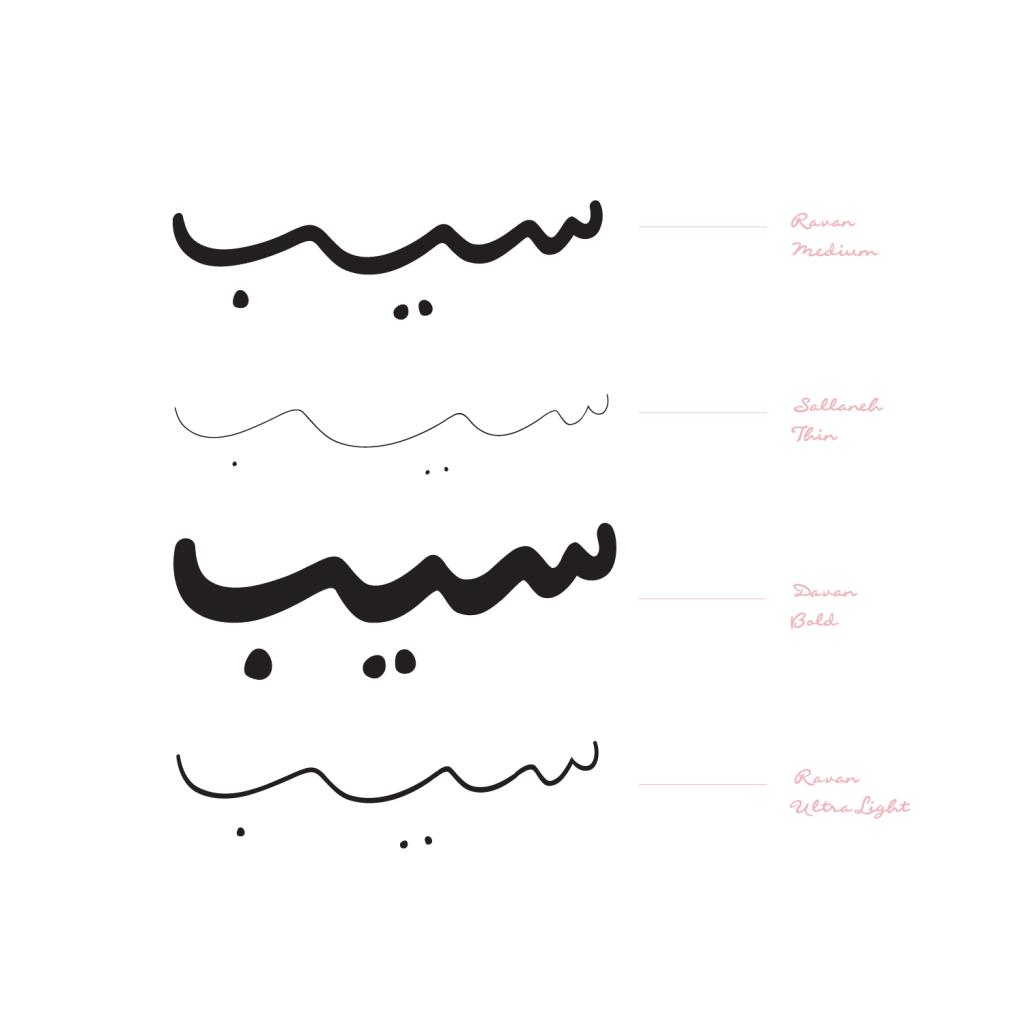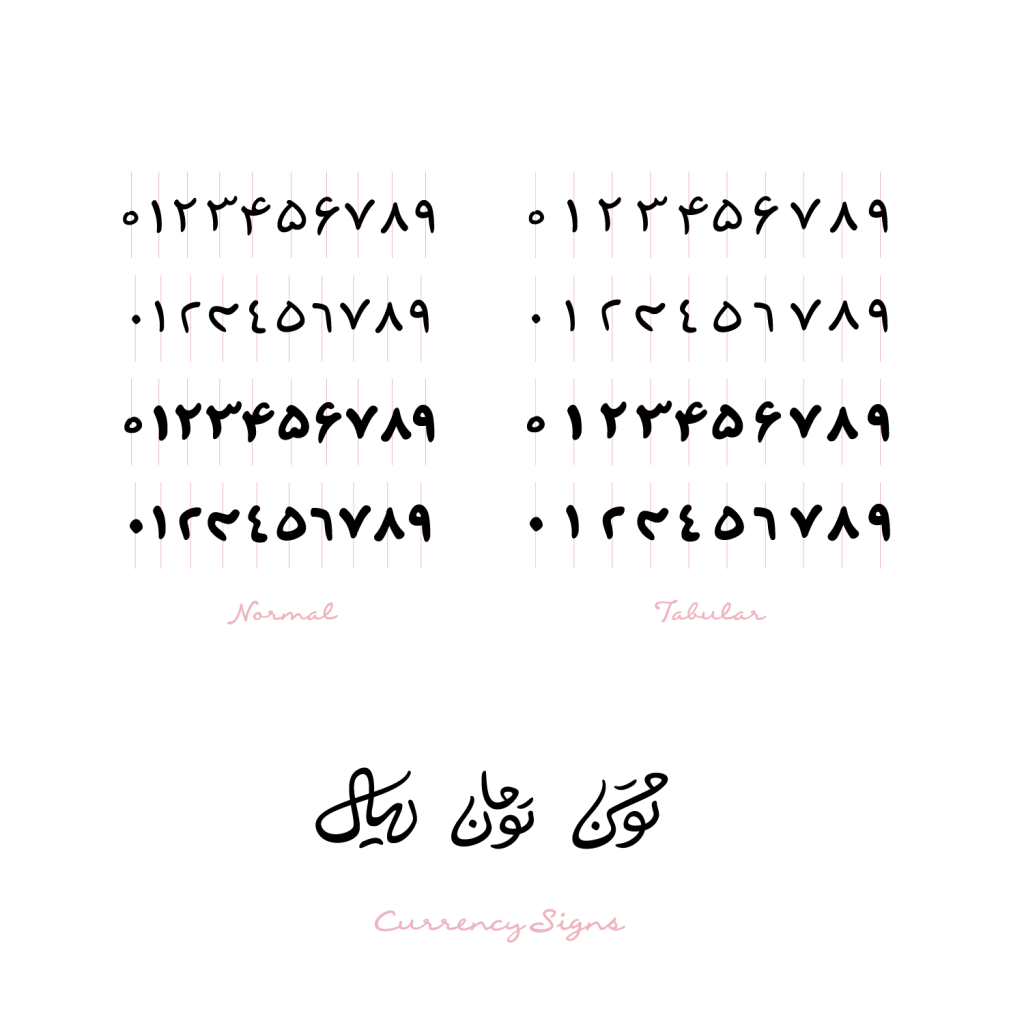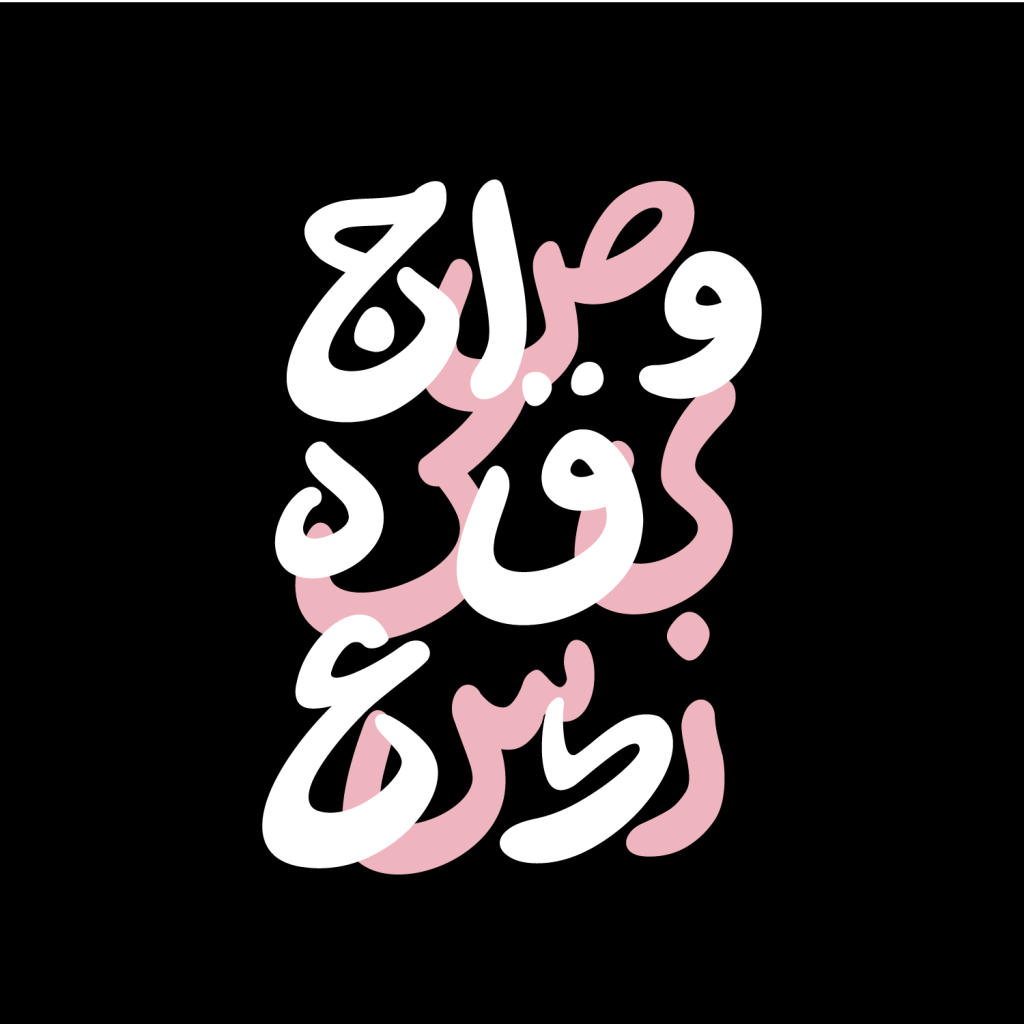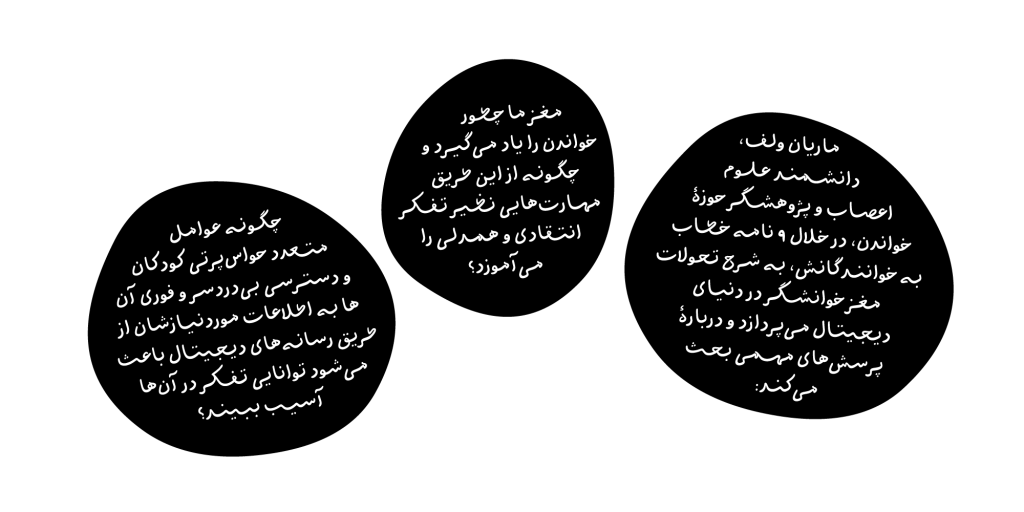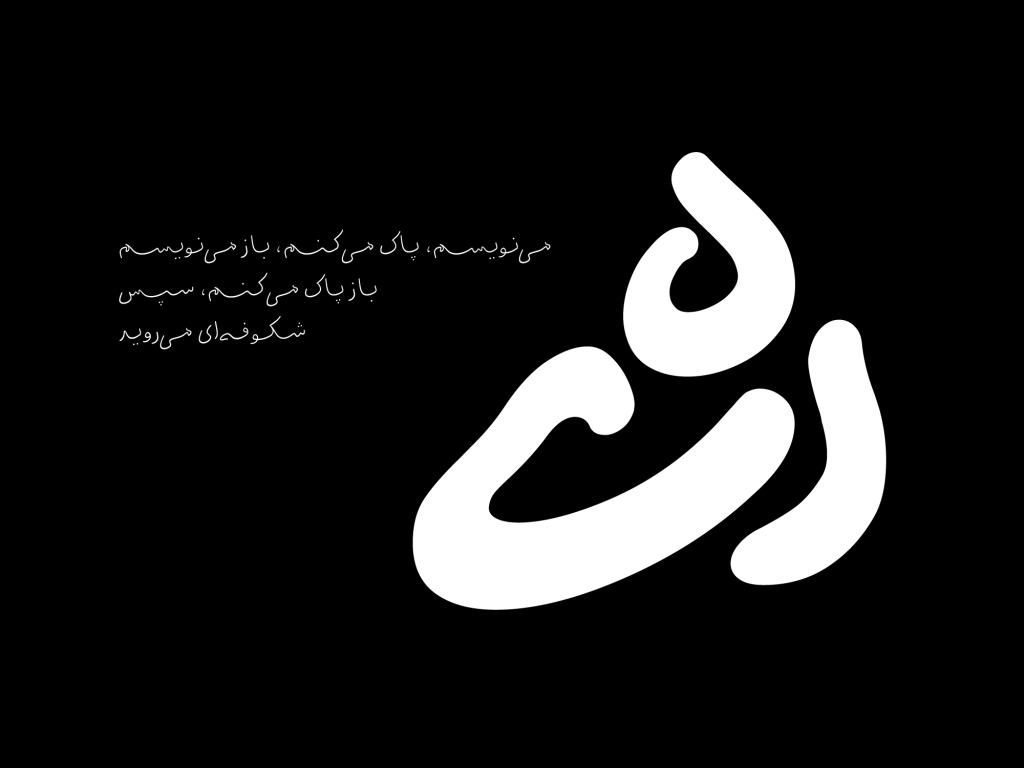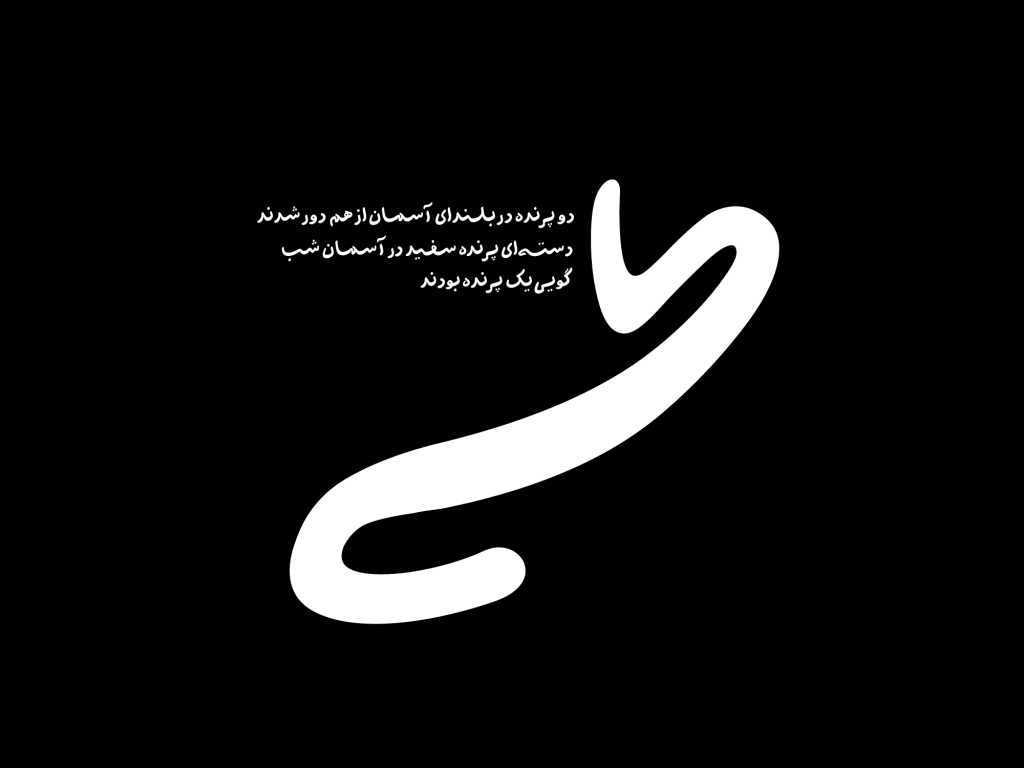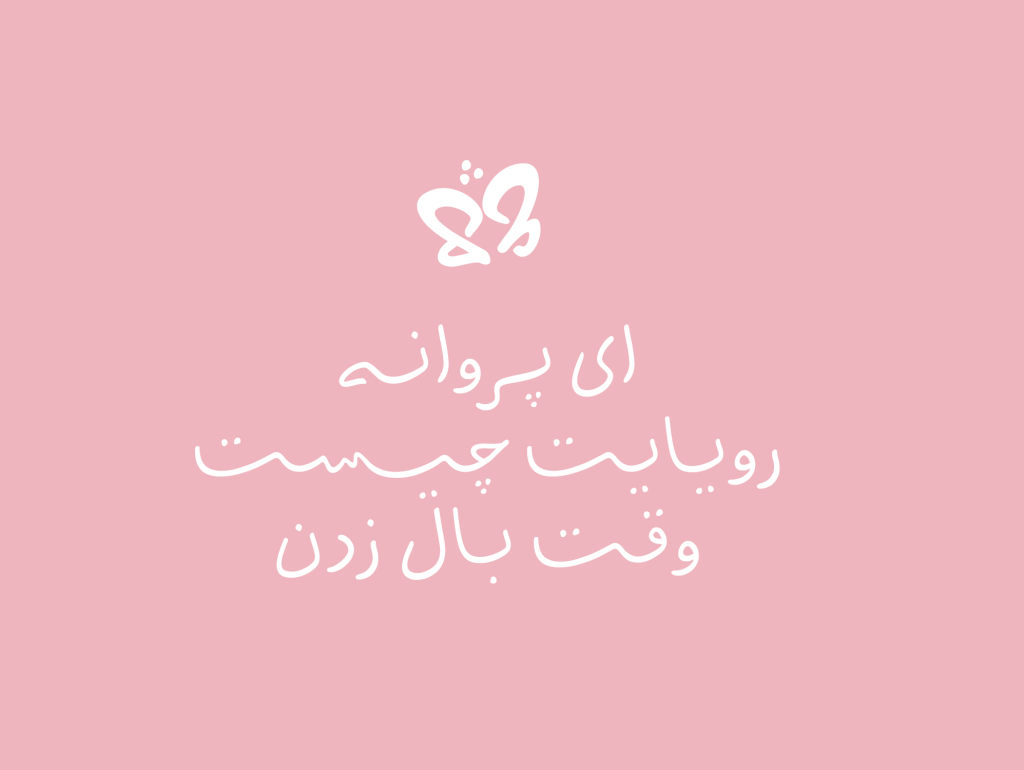
فونت هایکو – قلمی دست نویس
هایکو قلمی از دوره معاصر از خانواده خطوط دست نویس است که هم مناسب متن و هم مناسب برای عناوین می باشد . این تایپ فیس در دل خود اصالت، خیال و رویا، روایتگری، شوق و صمیمیت را یکجا دارد تا ذوق نویسنده را به تصویر بکشاند . اساس این قلم بر ویژگی اتصال و همنشینی حروف در شکلگیری کلمات خط فارسی متمرکز است. در عین پایبندی به سطر، از قالب حروفریزی و تایپ بیرون رفته و درجاتی از خوانایی و آشنایی را ایجاد میکند.
پشتیبانی هایکو از زبان های مختلف و نسخه وریبل
ضخامت (طیفی از مویی تا بولد) و سرعت (دوان/روان/خرامان/سلانه) از ویژگی های بارز هایکو هستند. اعداد به شکل معمول در میان متن و به شکل همعرض به کار می روند. همچنین نشانههای ریال و تومان در نسخه فعلی جانمایی شده اند. زبانهای عربی، کردی و اردو در این قلم پشتیبانی شده اند و برای متنهای چندزبانه کاراکترهای لاتین متناسب با کاراکترهای فارسی در آن اجرا شده است
از دیگر ویژگی های منحصر به فرد هایکو که به ندرت در سایر تایپ فیس های فارسی می توان یافت عنصر کشیدگی است . به این صورت که ابتدا مقداری کشیدگی برای ایجاد ریتم و خوانایی بصورت اتوماتیک و الگوریتمیک بین حروف تقسیم میشود و سپس کشیدگی کلمات شکل گرفته با همان تناسبات در محور کشیدگی قابل کم و زیاد شدن است. در نتیجه این ویژگی، کشیدگی به شکل ماشینتایپی در این فونت غیر فعال شده است.